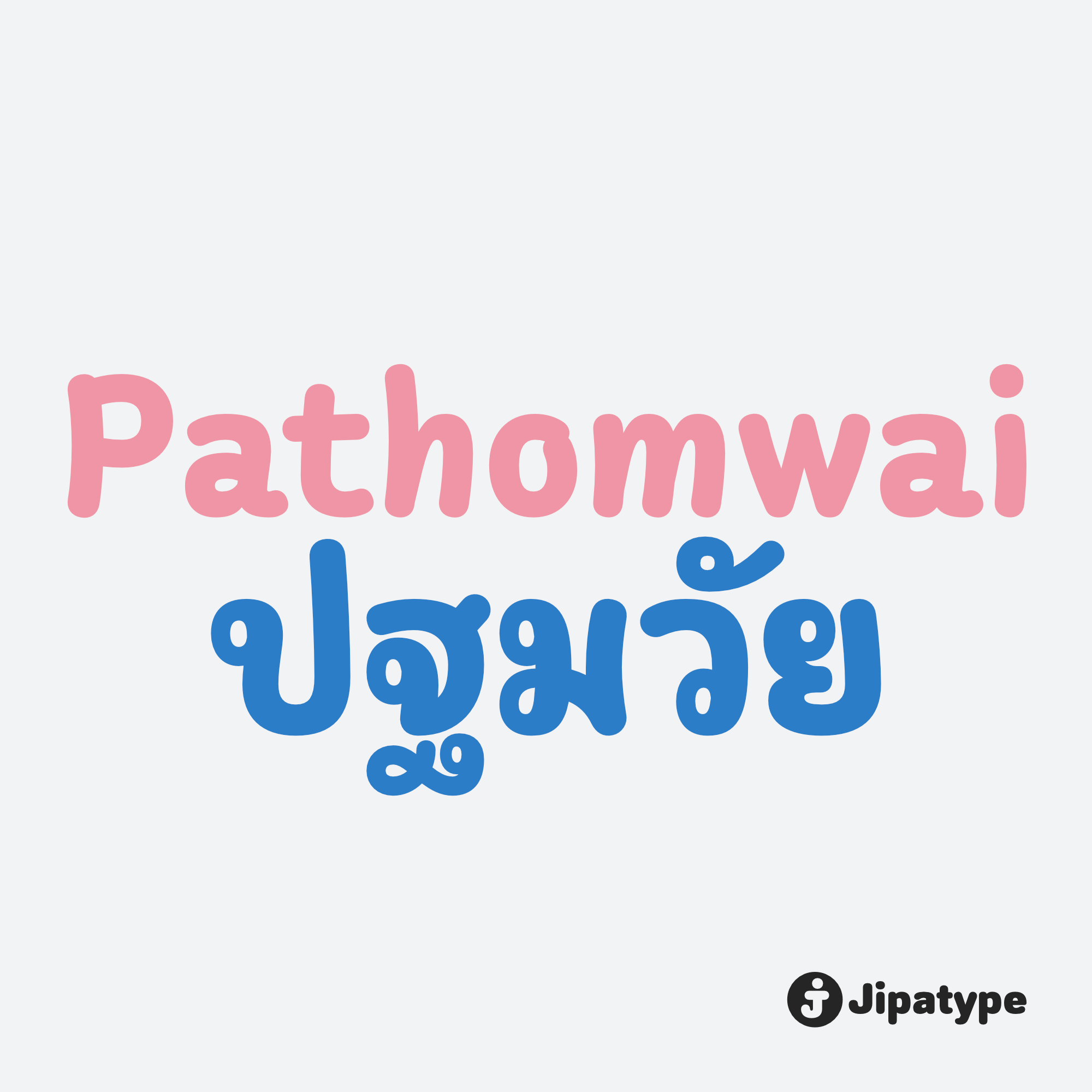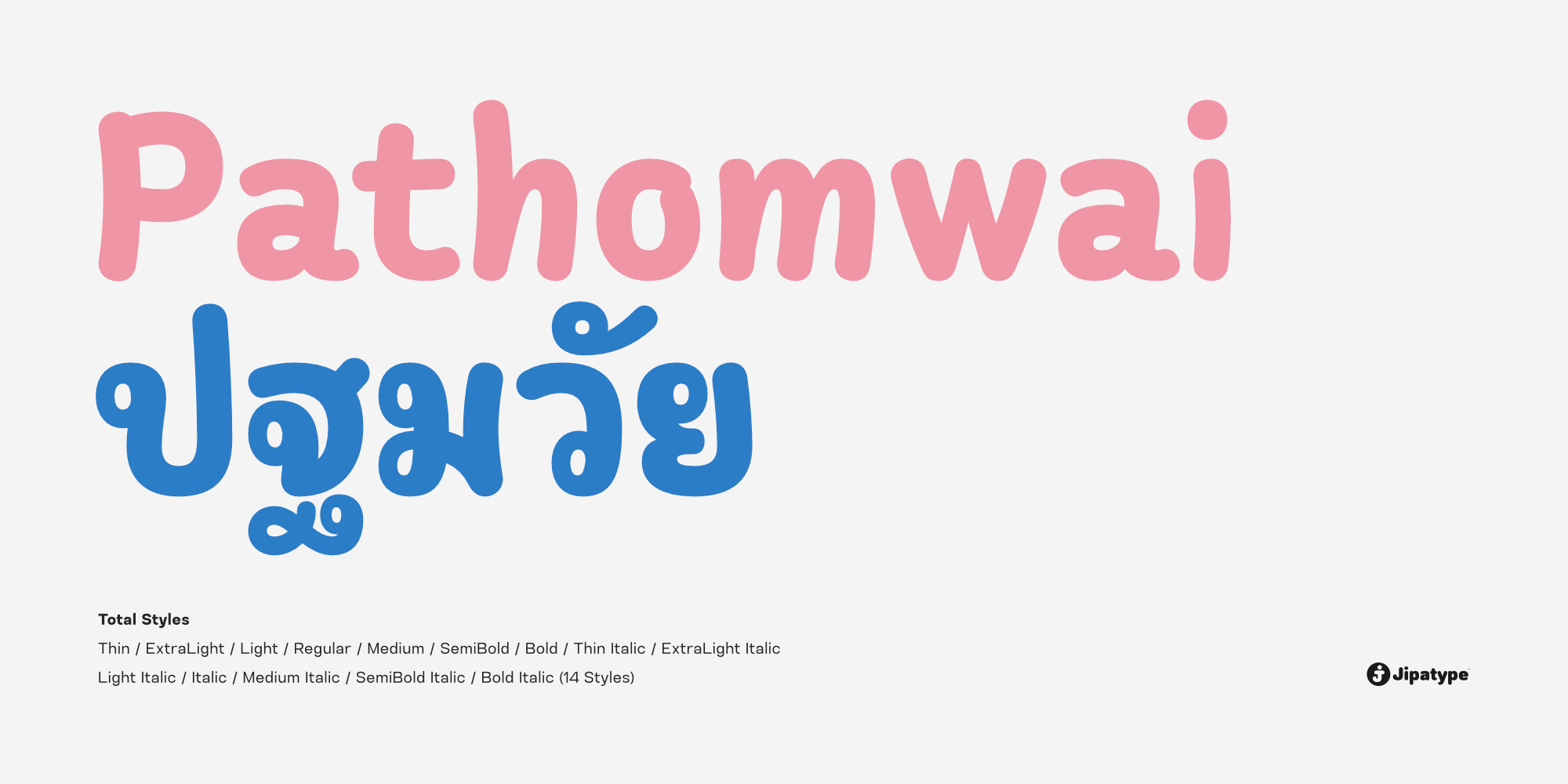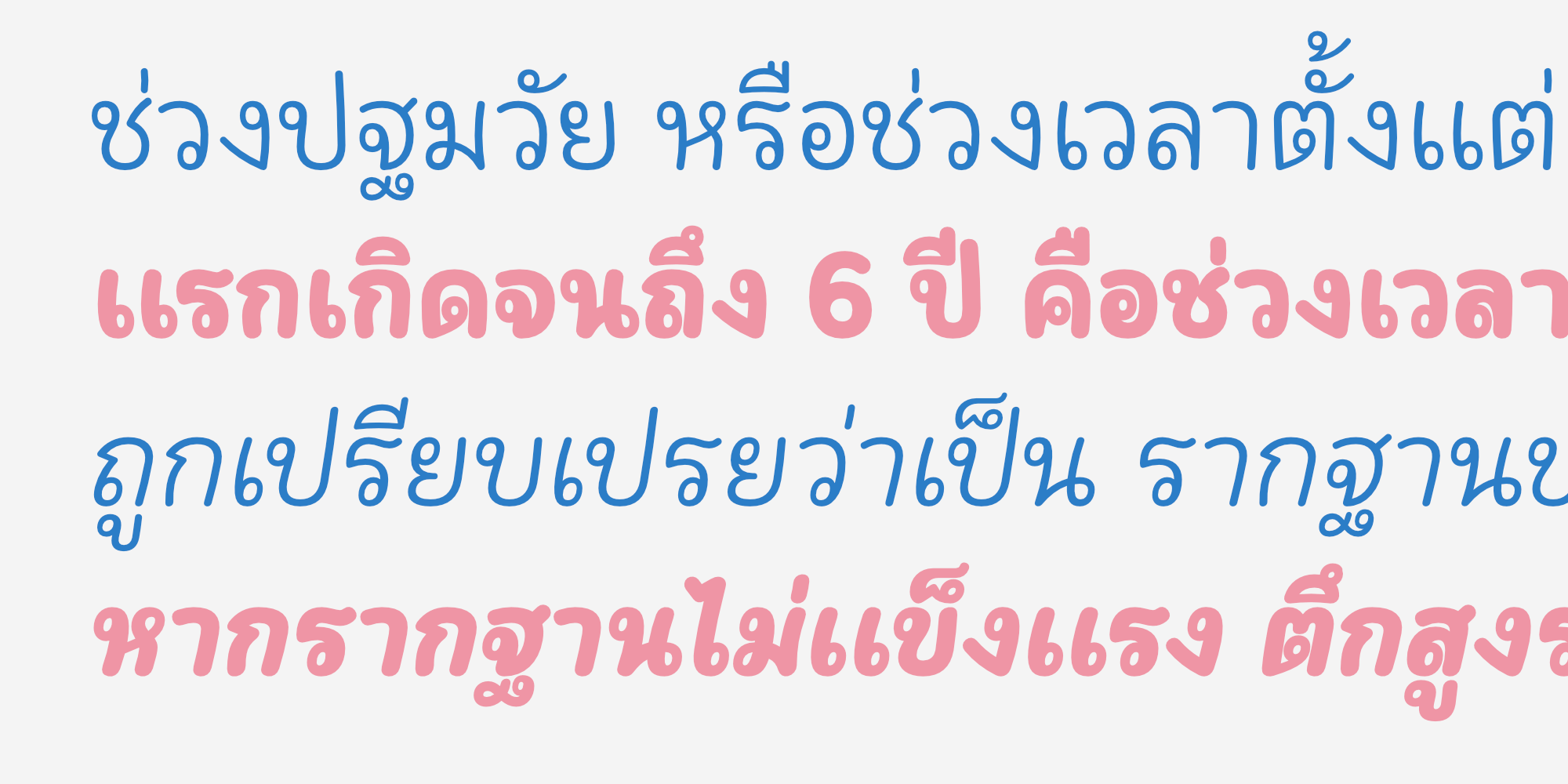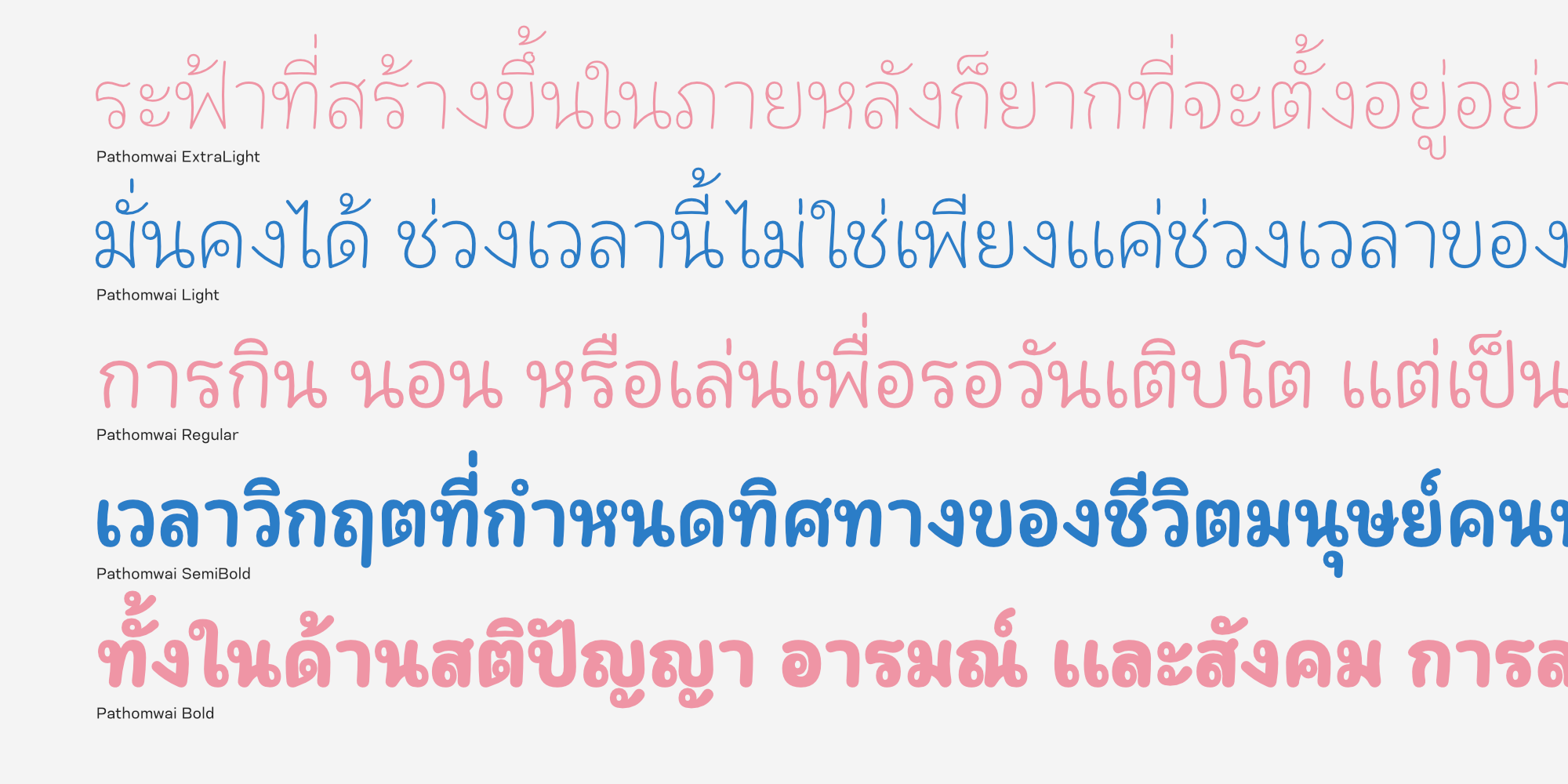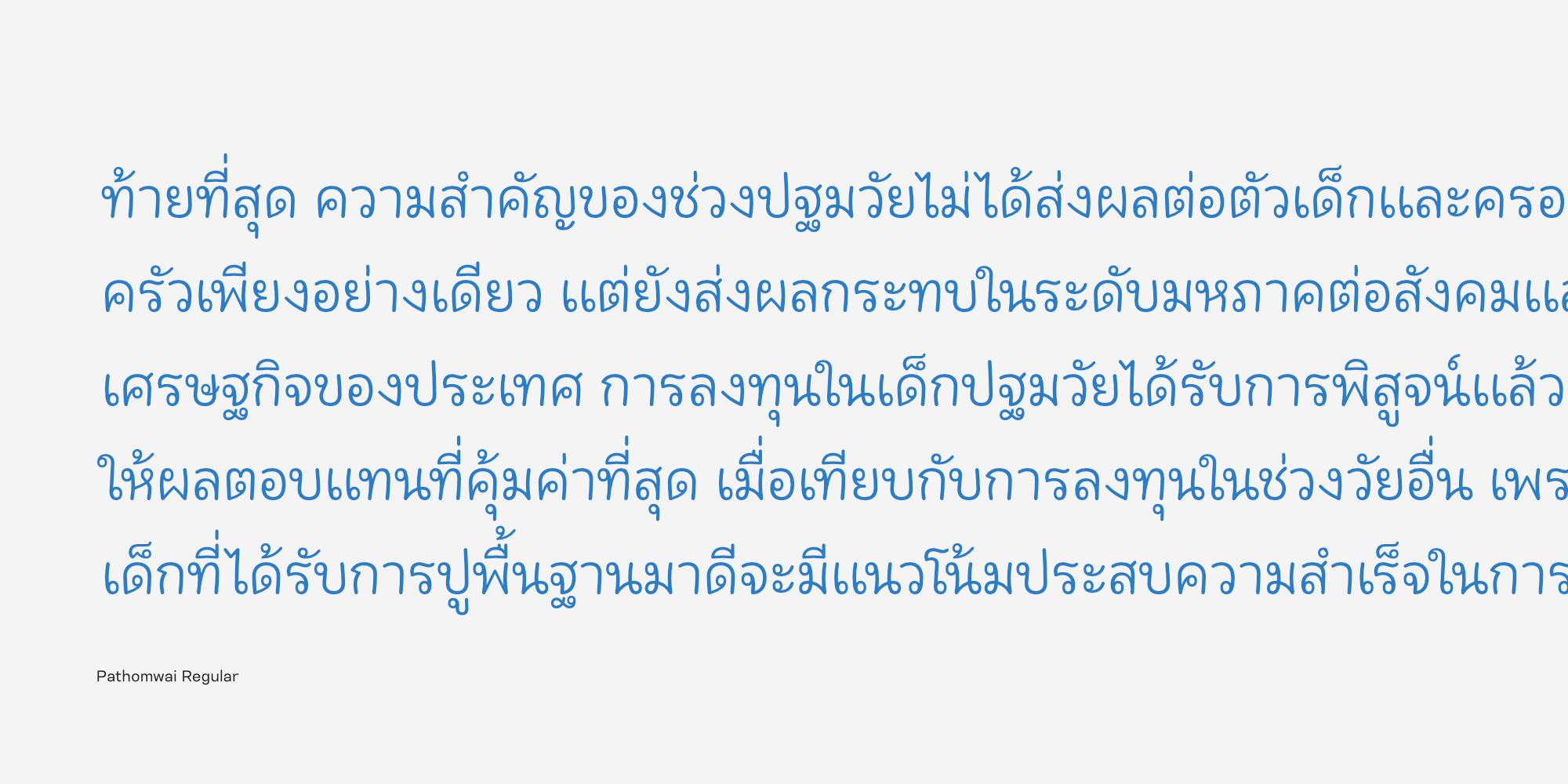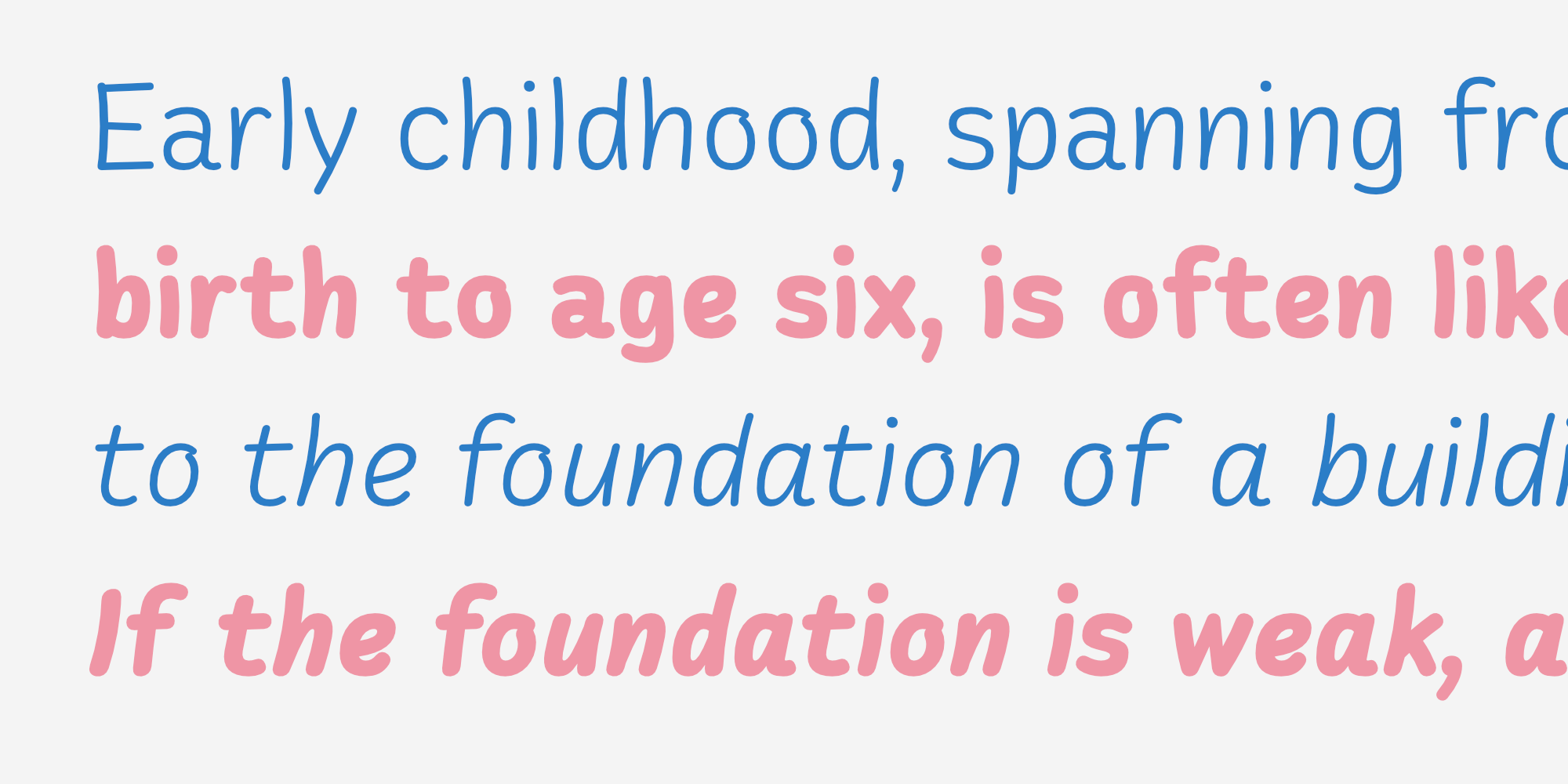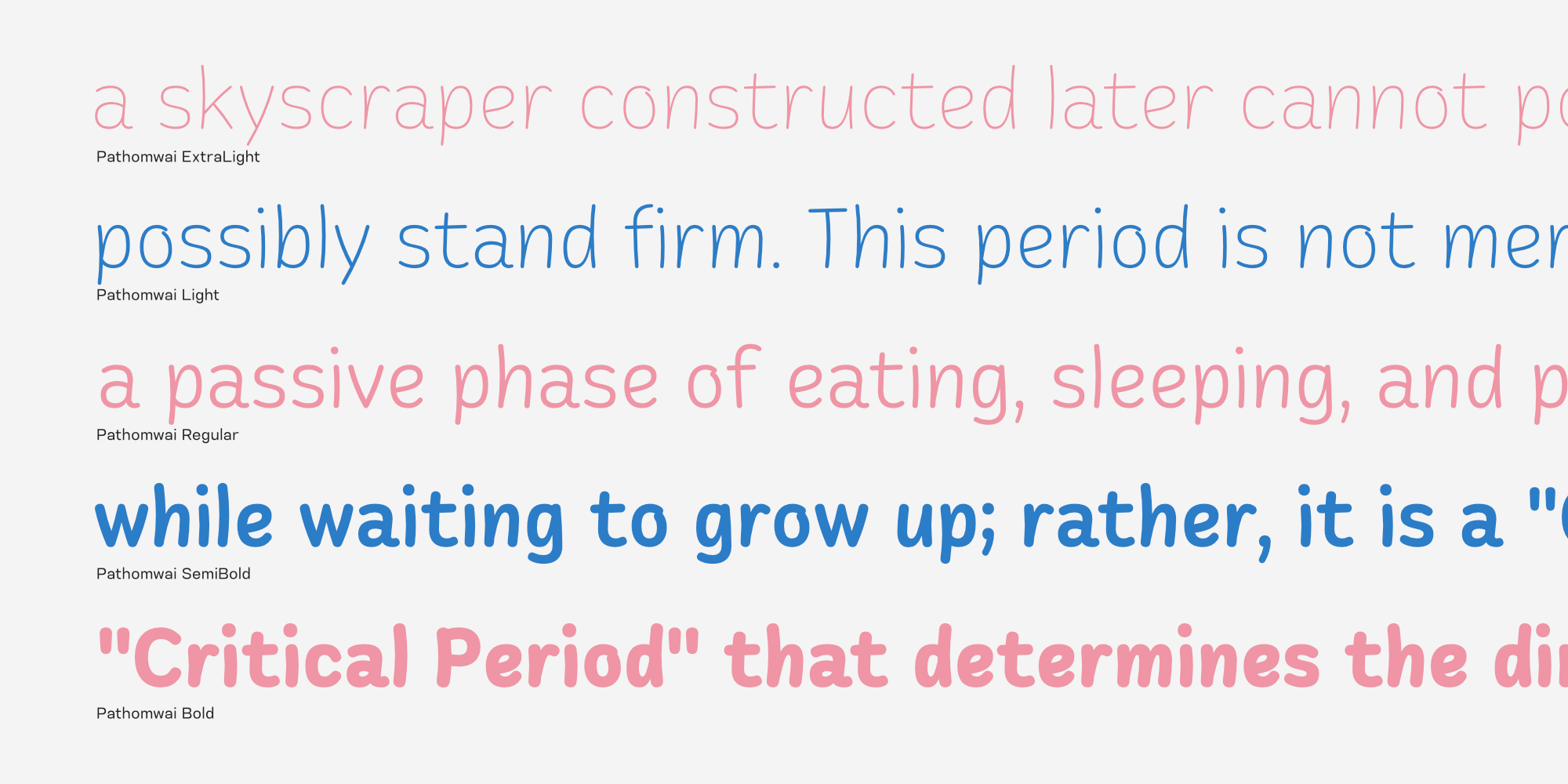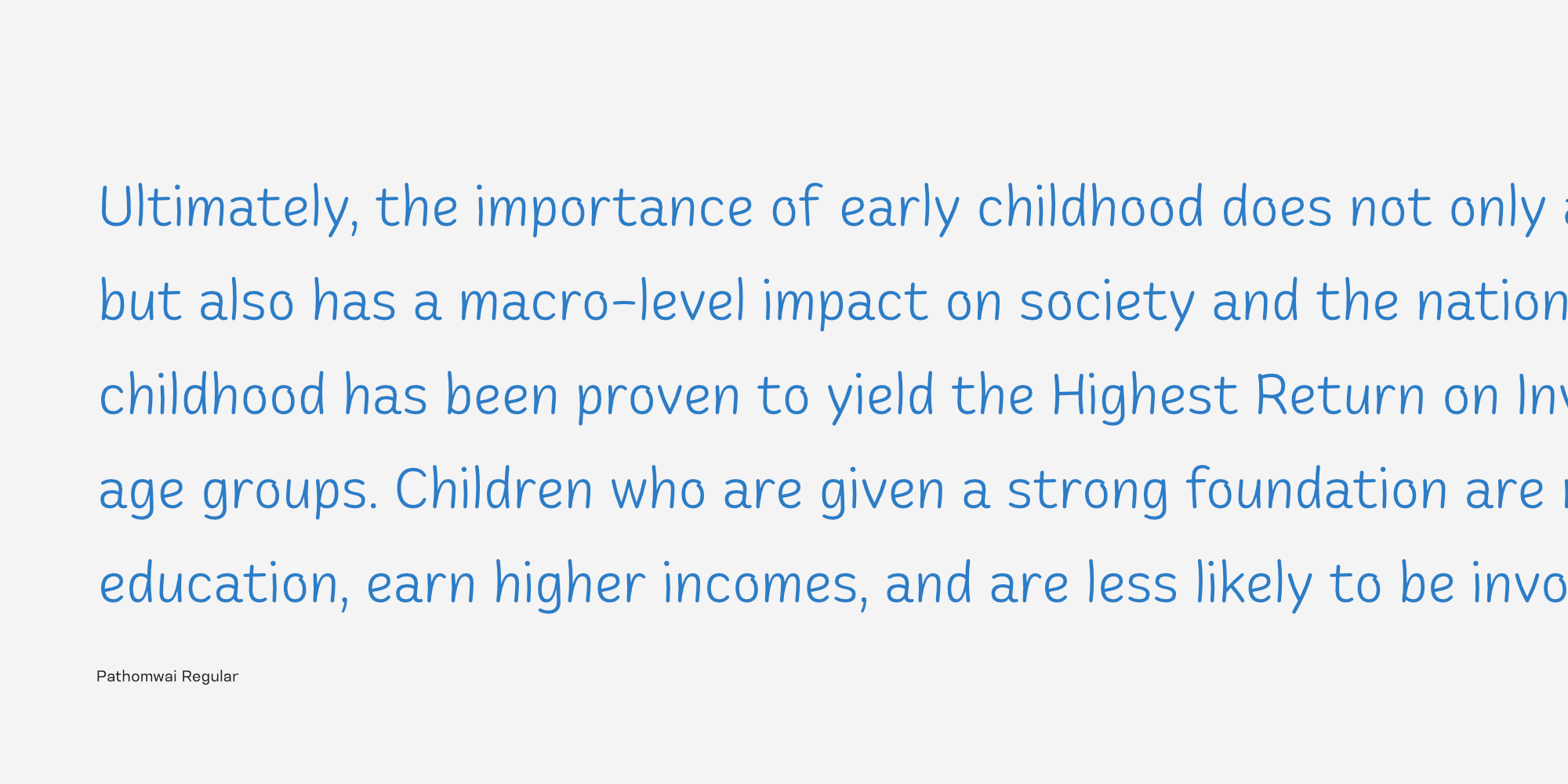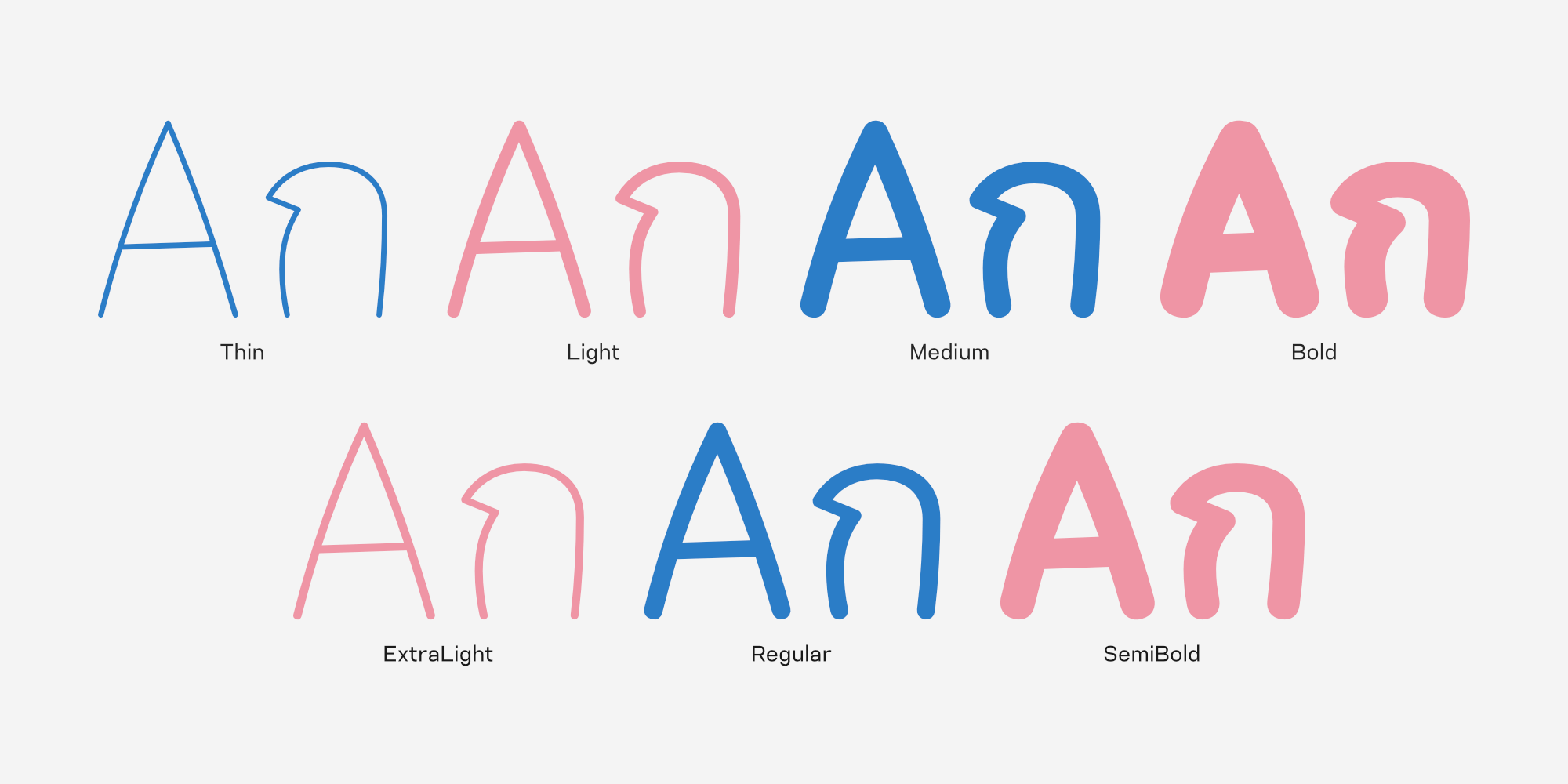
Pathomwai เป็นชุดแบบอักษรที่โดดเด่นด้วยรูปลักษณ์ที่ให้ความรู้สึกนุ่มนวล อบอุ่น และเป็นมิตรอย่างยิ่ง ตัวอักษรถูกออกแบบให้มีลักษณะปลายมน ทั้งในส่วนของตัวอักษรไทยแบบมีหัวและตัวอักษรละติน ลดทอนความแข็งกระด้างของเส้นสาย ทำให้ดูเหมือนลายมือที่เขียนด้วยปากกาหัวมนอย่างบรรจง
มีความอ่านง่าย สบายตา และดูสะอาดสะอ้าน โครงสร้างของตัวอักษรมีความกลมมน สื่อถึงความไร้เดียงสา ความขี้เล่น และความจริงใจ ผสมผสานระหว่างความเป็นระเบียบเรียบร้อยกับความอิสระของลายมือได้อย่างลงตัว
ด้วยบุคลิกที่ดูใจดีและเข้าถึงง่ายนี้ Pathomwai จึงเหมาะอย่างยิ่งสำหรับงานออกแบบที่ต้องการสื่อสารกับกลุ่มเป้าหมายครอบครัวและเด็ก เช่น หนังสือนิทาน, สื่อการเรียนการสอน, บรรจุภัณฑ์สำหรับผลิตภัณฑ์แม่และเด็ก หรือของเล่น
นอกจากนี้ยังสามารถนำไปใช้ในงาน Branding ทั่วไปที่ต้องการภาพลักษณ์ที่ดูเป็นกันเอง ผ่อนคลาย ไม่เป็นทางการจนเกินไป หรือใช้ในงานกราฟิกบนโซเชียลมีเดียที่ต้องการสร้างบรรยากาศที่ดูน่ารักและน่าเชื่อถือ
ออกแบบโดย : อานุภาพ ใจชำนาญ (Anupap Jaichumnan)